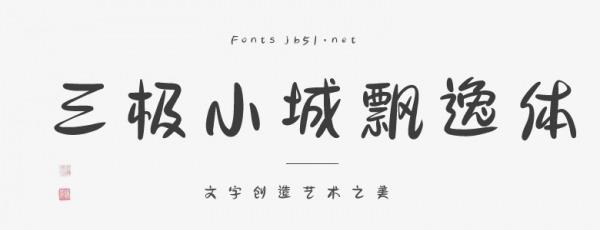
三極小城飄逸體簡(jiǎn)介:字形灑脫 連筆隨形變化 在行書(shū)的基礎(chǔ)上更靈動(dòng)多變,筆畫(huà)靈動(dòng)呼應(yīng)手寫(xiě)感十足,適合于文創(chuàng)產(chǎn)品 電影海報(bào)、包裝、品牌名稱(chēng)海報(bào)、媒體標(biāo)題 屏顯等。